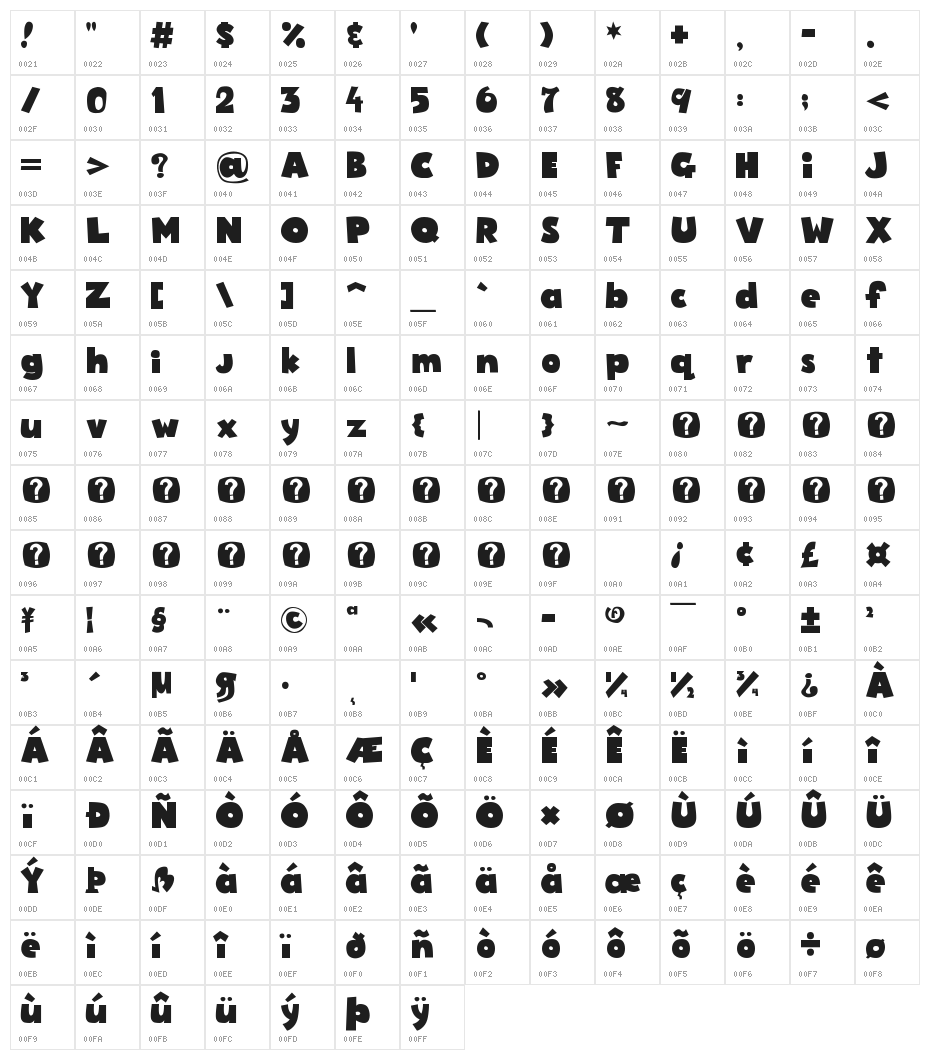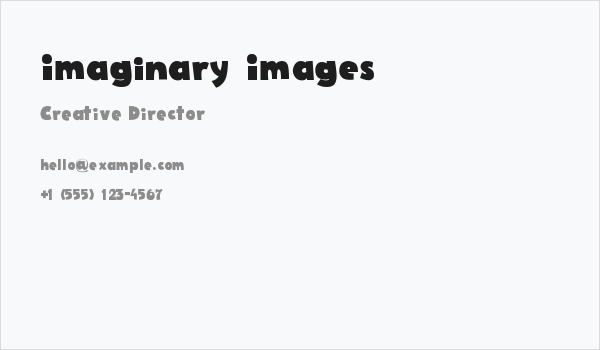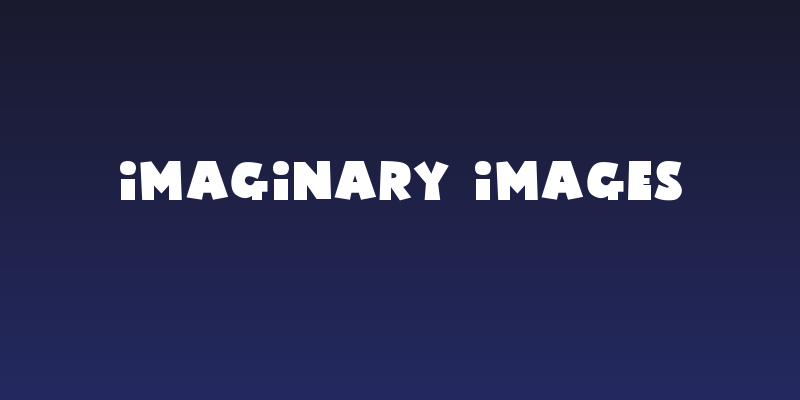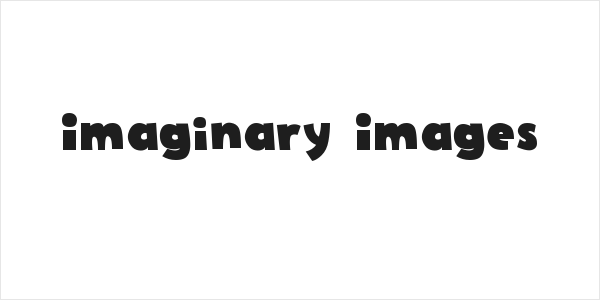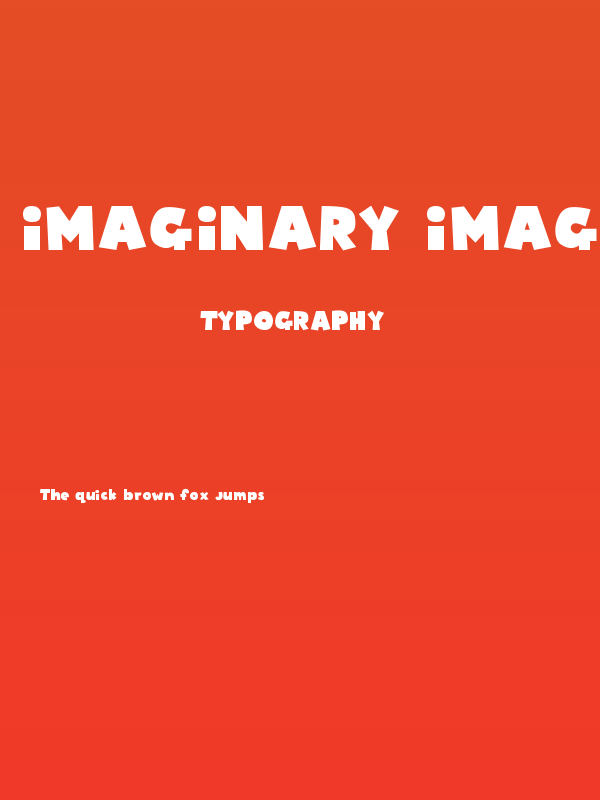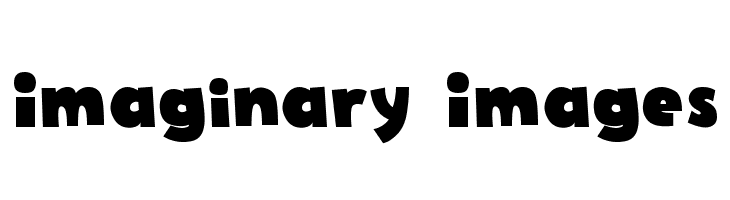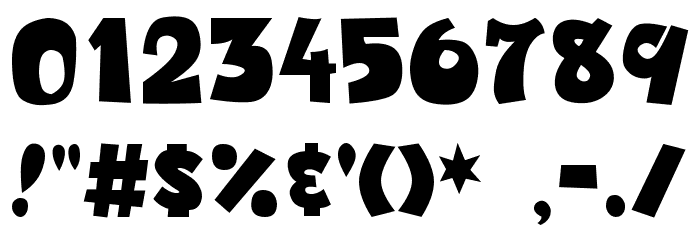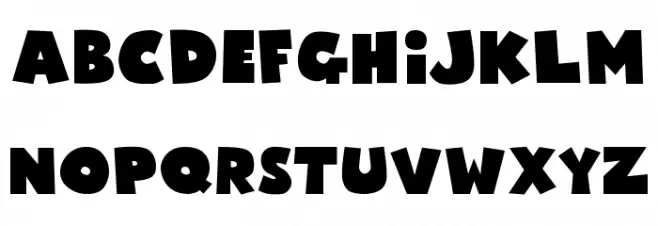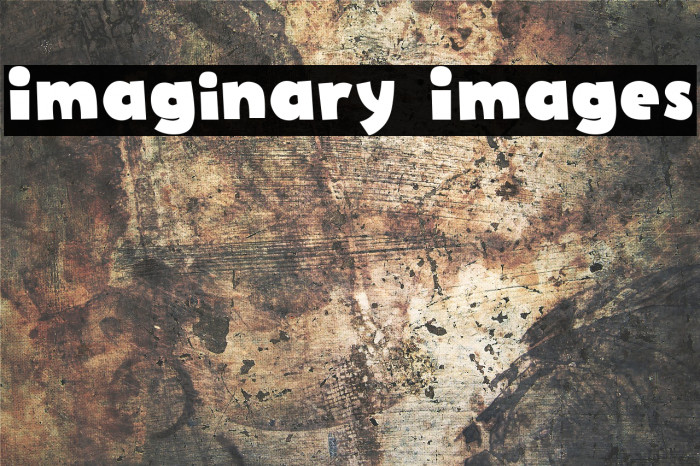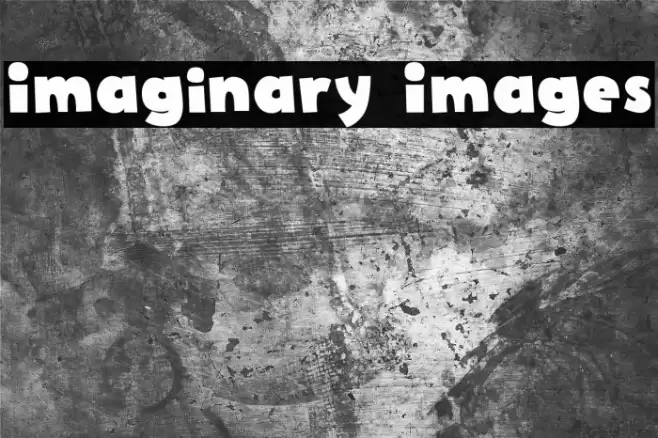
Imaginary Images Font
| Style général | Playful, Whimsical |
| Projets proposés | Ideal for children's books, playful branding, posters, and party invitations. |